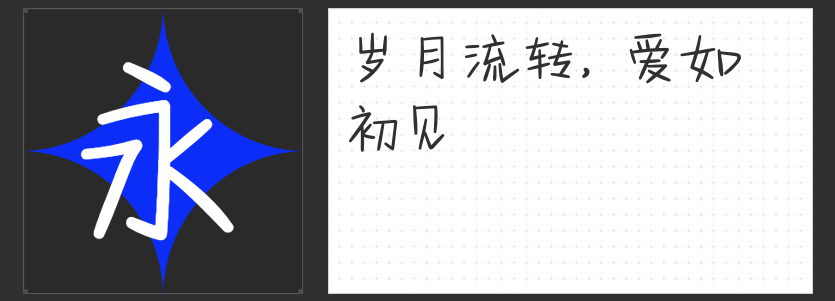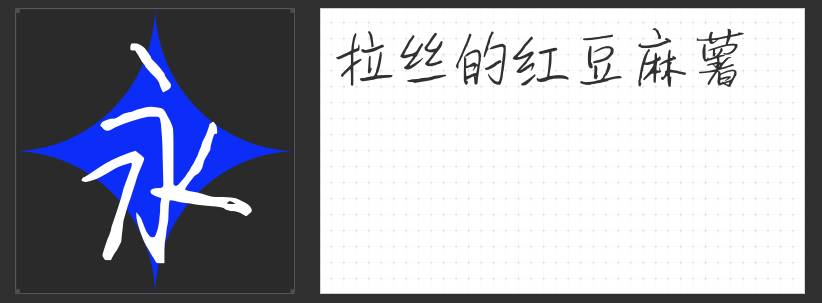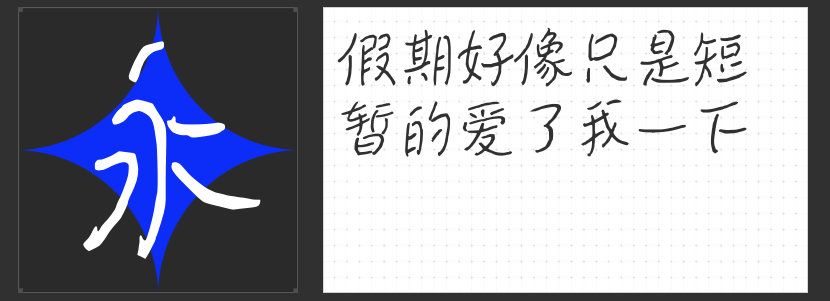
四款手写字体推荐:设计中的温度与灵动之选
在数字化设计日益追求效率与规范化的今天,手写字体的独特温度与人文气息成为打破同质化的关键。本文精选四款风格各异的手写字体,它们以自然笔触传递情感,以灵动结构激发创意,为商业海报、包装设计、新媒体内容等领域注入鲜活生命力。
一、励字造仲夏简 常规
这款字体以传统书法为根基,融入现代设计审美,形成刚柔并济的独特气质。笔画坚挺爽利,边缘保留手写特有的斑驳质感,钩笔处随性洒脱,既传递出手写的力量感,又不失文艺清新。其字形端正均衡,通用性极强——无论是商业海报中需要突出主题的标题,还是包装设计中传递品牌调性的短句,亦或是短视频字幕与新媒体配图的动态呈现,都能以自然笔触与场景形成情感共鸣。
二、贴仔初恋体
这款字体仿佛从青春情书中跃然而出,笔画间流淌着未经雕琢的纯真感。俏皮的转折与工整的结构形成微妙平衡,既保留手写的随意性,又通过精准的笔画控制确保可读性。其独特气质使其成为传递温暖、治愈或轻幽默内容的理想选择,尤其适合需要营造亲切感与记忆点的设计场景。
三、MyFont求假期简 细体
以“作业本字体”为灵感,这款细体通过柔软圆润的笔画构建出亲切无害的视觉语言。无刻意装饰的设计反而成就其高辨识度,仿佛能唤醒观者对学生时代的集体记忆。其简洁结构与温和气质,使其成为需要传递轻松、自然氛围的设计的优选,例如儿童产品包装、生活类内容配图等。
四、MyFont自由简 细体
这款字体以自由灵动的用笔诠释手写精髓,笔画间蕴含鲜明的节奏感与韵律美。细腻的线条如行云流水,字形简洁却富有变化,在保持高辨识度的同时,赋予文字动态美感。其优雅清新的气质,使其既能独立作为设计焦点,也可与图形元素巧妙融合,为品牌视觉系统注入艺术气息。
四款字体虽风格迥异,却共同以手写特质突破机械感,为设计注入人文温度。无论是追求传统与现代交融的层次感,还是渴望青春记忆的情感共鸣,亦或是需要自然灵动的视觉表达,这些字体都能以独特笔触,帮助设计师在商业与艺术的平衡中,创造更具温度与生命力的作品。